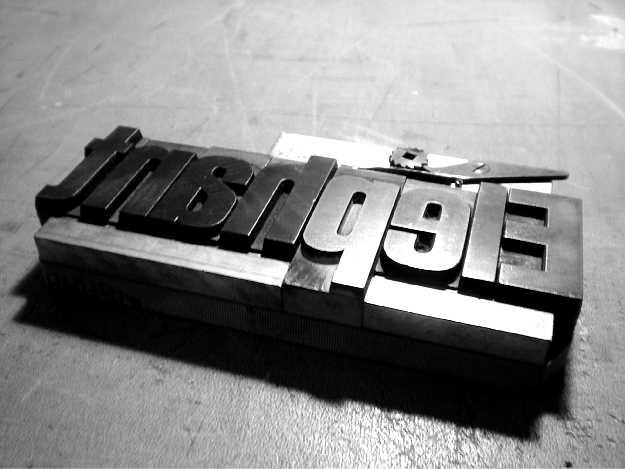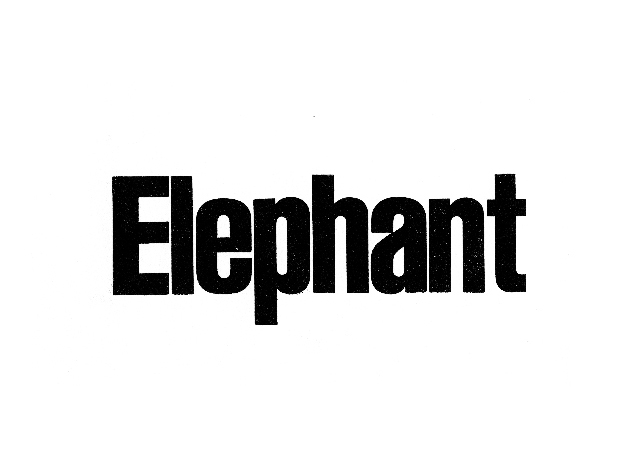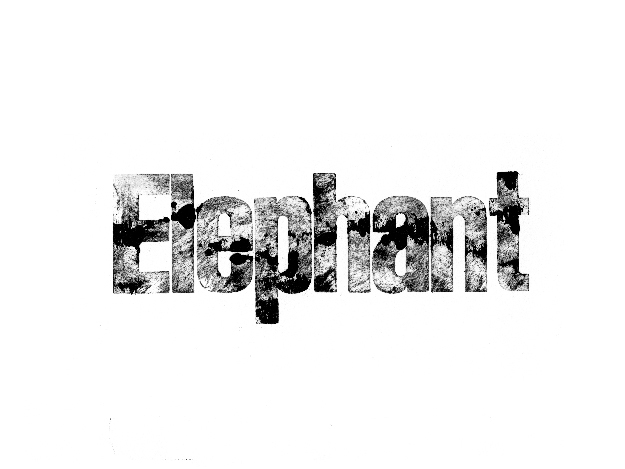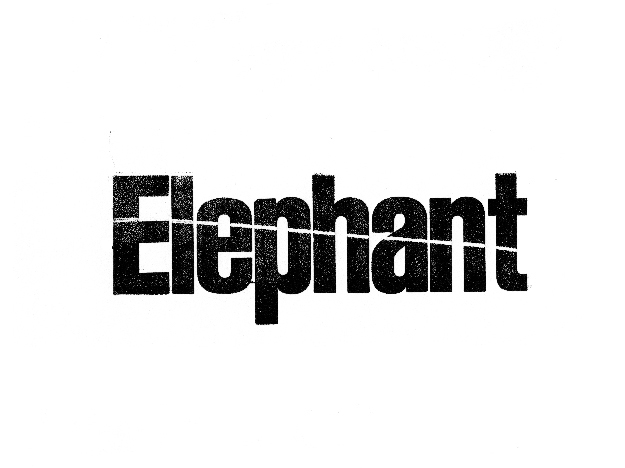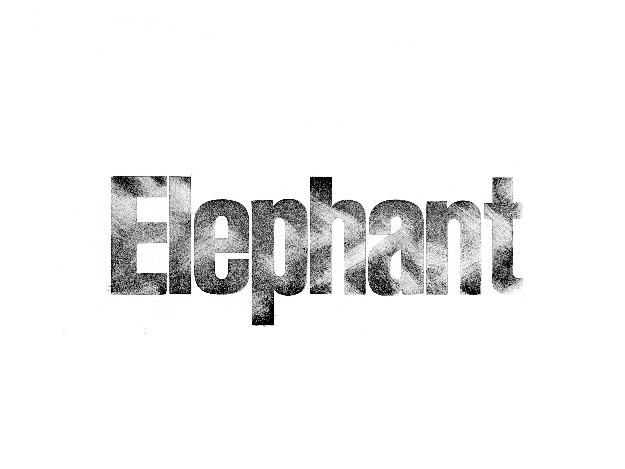
Wood type
発想の起源
木活字を使って印刷したときに1つだけおおきな亀裂のはいっているものがあった。「そんな活字だとせっかくのデザインがよくないね」といわれたときにタイポグラフィについても未熟だったし使えなくなった活字を見ながらお互い未完成だねとおもった。
偶然にも、キズが入っている活字の持っている個性を発見した。活字面に均一にインキがのらないことと同じように、印刷できないことは活字として失格なのだけれど、そこにはかけがえのない美しいものがあった。そのことがあって、「木活字にインキを塗布する方法によって別の印象を与えることができるのではないか」と考え、実験をはじめた。
木の活字にキズつけてしまっては何度も使用、実験できないためもっと簡単に活字面にたくさんのバリエーションで表情を持たせる方法はないだろうか…これがこのプロジェクトの発想の起源となった。